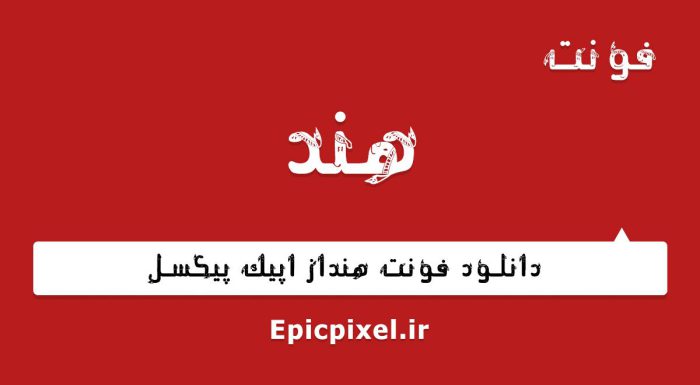
3 فونت هند فارسی
دانلود مجموعه کامل فونت Hend فارسی Font هند |
| ⭐ مجموعه فونت | دانلود فونت فارسی هند بولد Font Hend Bold ام زد هند رگولار Mz Hend Regular دبلیو هند ریگولار W Hend Regular |
بیسش از نود درصد شبیه فونت سرخپوست هستش